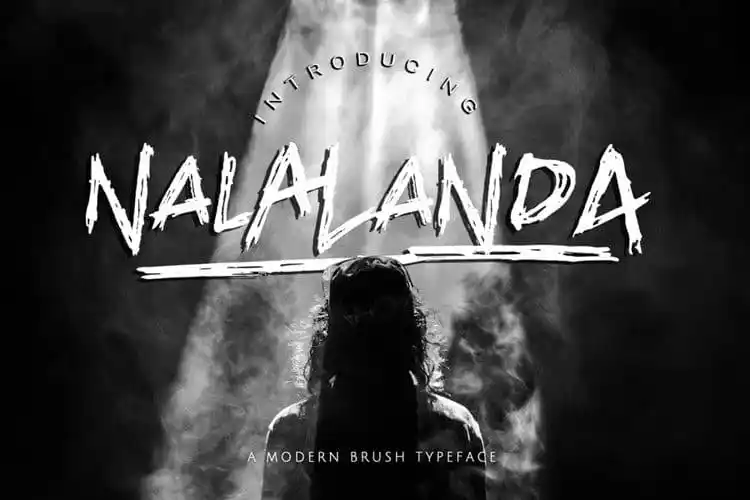
Nalalanda Brush Font – Fonte Grátis
Nalalanda Brush Font
A Nalalanda Brush Font é uma excelente escolha para aqueles que procuram personalidade e expressão forte em suas criações digitais. Com a sua estrutura natural de traço de pincel, passagens rápidas e detalhes afiados, essa fonte se destaca como um recurso perfeito para artigos gráficos criativos, especialmente para tópicos relacionados a esportes e fantasia. Suas características incluem estilos alternativos, traços embolinchados e sublinhado, o que permite uma grande flexibilidade na sua aplicação. Perfeita para designs de camisetas, capas de jaquetas, postagens em outdoors, ou qualquer outro elemento que busque um forte impacto visual. A Nalalanda Font é a escolha ideal para quem busca expressar seu próprio estilo e criar uma marca única no mundo digital.